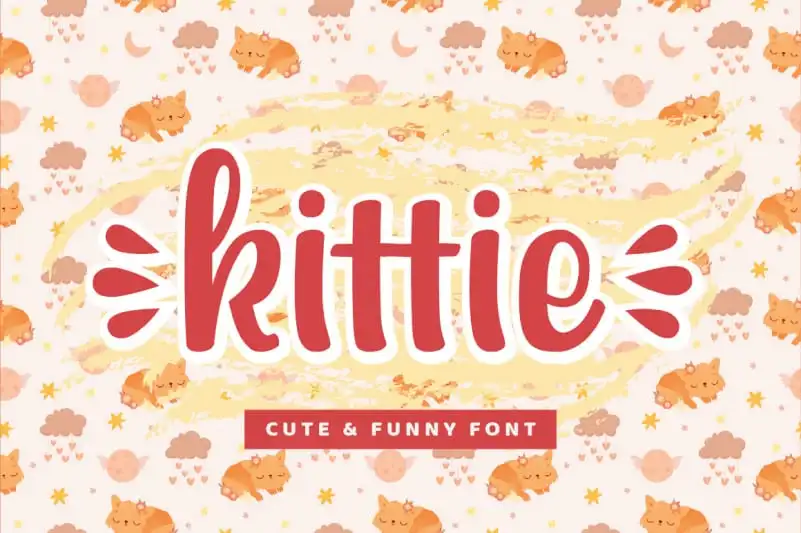
kittie Display Font – Fonte Grátis
kittie Display Font
A fonte Kittie Display Font é uma escolha perfeita para quem procura uma mistura única de estilo alegre e descompromissado. Ideal tanto para letraversagem quanto para criações digitais, esta fonte é uma opção elegante que traz um ar descontraído às suas ideias. Com um gosto leve e encantador, ela oferece uma linguagem vibrante e colorida, certamente adorada pelos criadores de designs digitais em busca de algo agradável e moderno. Composta por linhas fortes e uma escrita autêntica de mão, essa fonte é perfeita para criar um toque divertido em qualquer projeto ou layout gráfico, levando-os ao próximo nível. Para quem deseja dar vida à sua arte com uma escolha única e descontraída, o Kittie Display Font provavelmente será a fonte certa para explorar.